艺术海报字体通常为报刊的大标题或者小标题,普通的文章中也有所应用,它的突出特点便是表现力优于普通字体,比横平竖直的宋体和略带弯曲的篆体更加粗壮和浑厚,所以艺术字体也被称为广告行业的标配,它的互动性强,个性魅力爆表,那么艺术字体海报为什么深受广告行业的青睐呢?
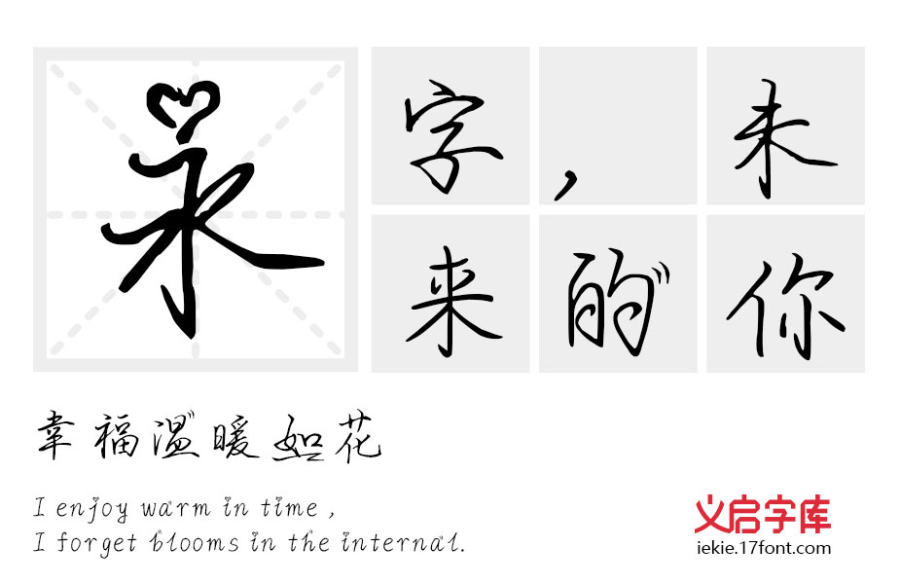
所谓的图形化艺术字创意就是在艺术字中融入恰如其分的图形,通过图形的融入让艺术字画面更有趣,更有想象空间。如:单纯的设计钢笔线条是非常容易设计的,也许两分钟就可以搞定,但是只有在它的图形上面加入更多的元素和创意,才能让这个艺术字更有想象空间,更有画面感,义启字库的艺术创意字体海报所表现的不仅仅图形,而是带有一种特殊的个性化寓意。
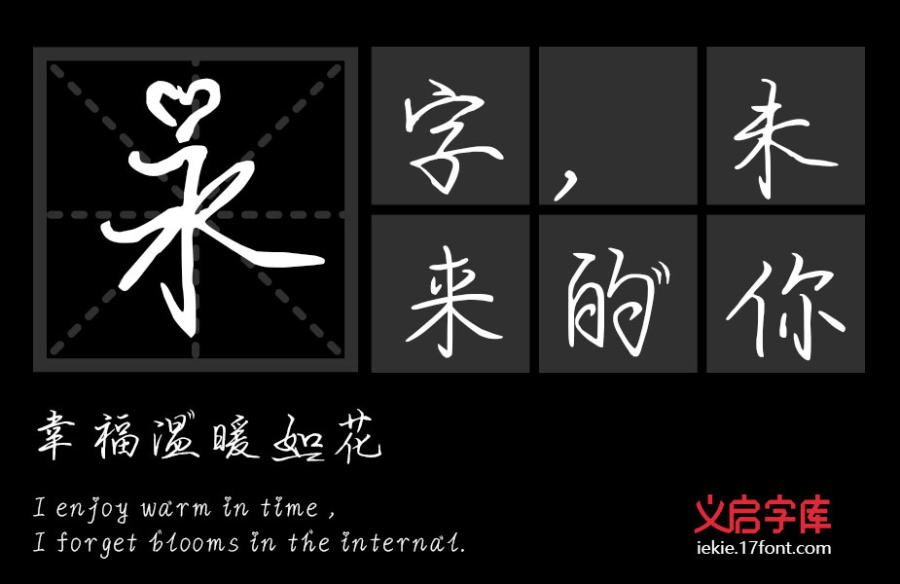
一些艺术字体海报融入了大量的螺旋形的曲线,联想到可爱这个词,皇冠之类的图形放在这里也非常恰当,然后通过螺旋线条的符号把艺术字穿插起来显得比较可爱,比较有趣,这使用螺旋线条在AI里很轻松的实现。再比如汪星球字体,充分利用方形的笔画结构,可做类似于星球的图形,然后加入图形角,再简单描边这个艺术字就很轻松的完成了。
在艺术字体海报中并非遵循传统的字体,它的突出设计大胆,有流畅洒脱也有明快矫健,甚至在许多牌匾匾额中都有所应用,其艺术韵味明显升高。